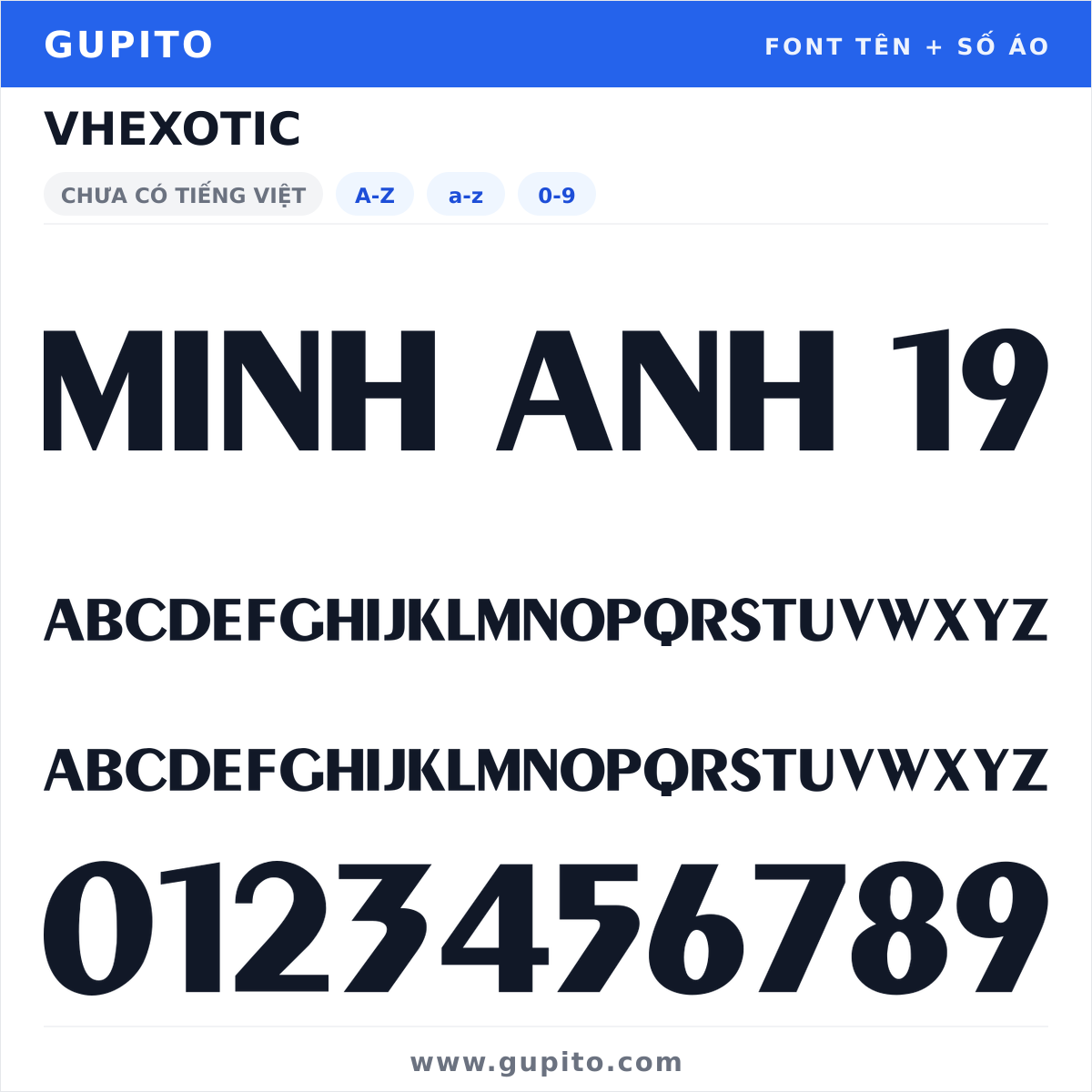
.VnExoticH Normal
.VnExoticH Normal · Font VHEXOTIC in tên áo bóng đá, số áo thể thao · đậm vuông vắn
Font VHEXOTIC với nét chữ đậm, vuông vắn, thích hợp in tên và số áo bóng đá, áo lớp, quà tặng. Có bảng chữ cái và số đầy đủ. Bộ chữ .VnExoticH Normal dùng để in chuyển nhiệt lên áo đấu, áo lớp, áo nhóm và đồ thể thao theo yêu cầu. Kiểu dáng: đậm vuông vắn. Font dùng cho chữ không dấu và số áo. Có đủ bộ chữ số để in số áo. Từ khoá liên quan: font vhexotic, font in tên áo, font in số áo, font áo bóng đá, font áo thể thao, font chữ đậm, font vuông vắn, font có bảng số.